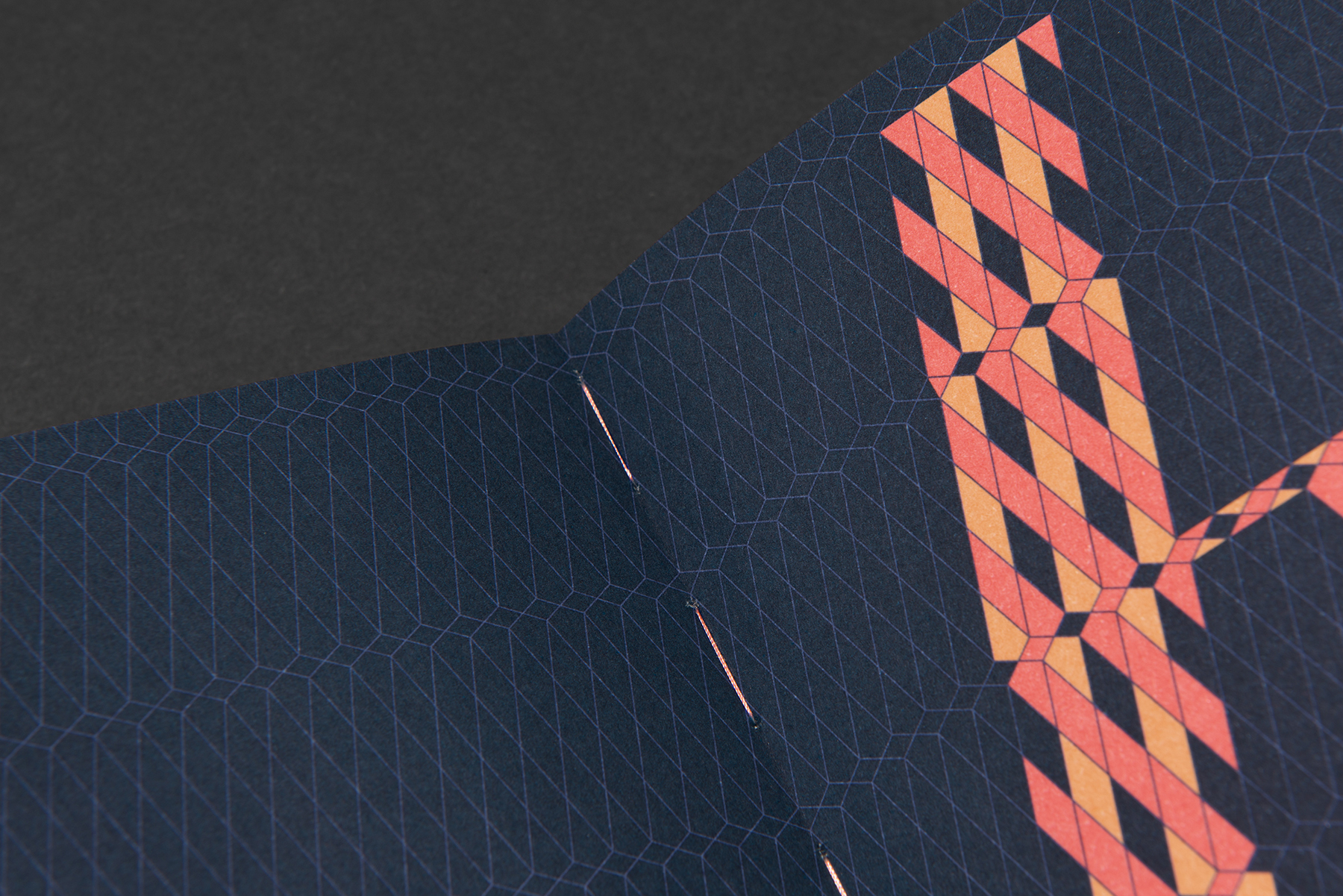
1826 days – The five years plan
5 Jahre sind 1826 Tage. Der Planer lädt dazu ein Gedanken, Erlebnisse und Pläne zu dokumentieren. Eine Seite für jeden Tag des Jahres, die ganz individuell genutzt werden kann. Vor jedem Monatskapitel befindet sich eine Seite zur Reflektion des vergangenen Monats und eine für die Vorhaben des kommenden. Über einen Zeitraum von 5 Jahren, von 2023 bis 2027, kann man nicht nur vergleichen, was man an demselben Tag vor 1, 2, 3 oder 4 Jahren gemacht hat, sondern kann auch längerfristig seine Ziele, Wünsche und Gedanken verfolgen.
Produziert von der Druckerei Thieme Meißen auf Fedrigoni Papieren. 432 Seiten, die in 8 ausdrucksstarken Pantone Sonderfarben gedruckt wurden, vereint in einer offenen Fadenheftung und akzentuiert durch einen Farbschnitt: ein ganz besonderer Wegbegleiter.
Der Kalender ist das Ergebnis einer Kooperation der Druckerei Thieme Meißen & typoint.
Die Gestaltung des »5 Jahre Planer« stammt von Johanna Höflich und Patrick Marc Sommer.
Die Gestaltung basiert auf einem Raster mit 5 Zeilen für 5 Jahre. Die vertikale Unterteilung steht für die 12 Monate, so dass sich ein Raster ergibt, das die Gestaltung prägt: Die Zahlen auf den Monatstrennseiten entspringen diesem Raster und unterstützen die Orientierung.